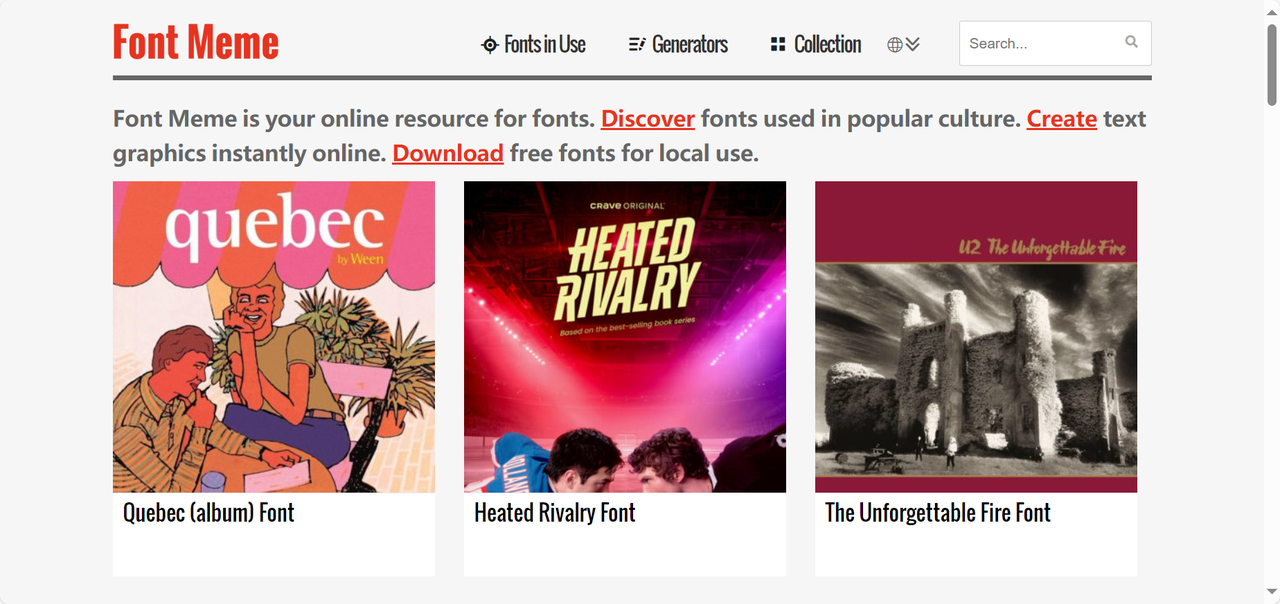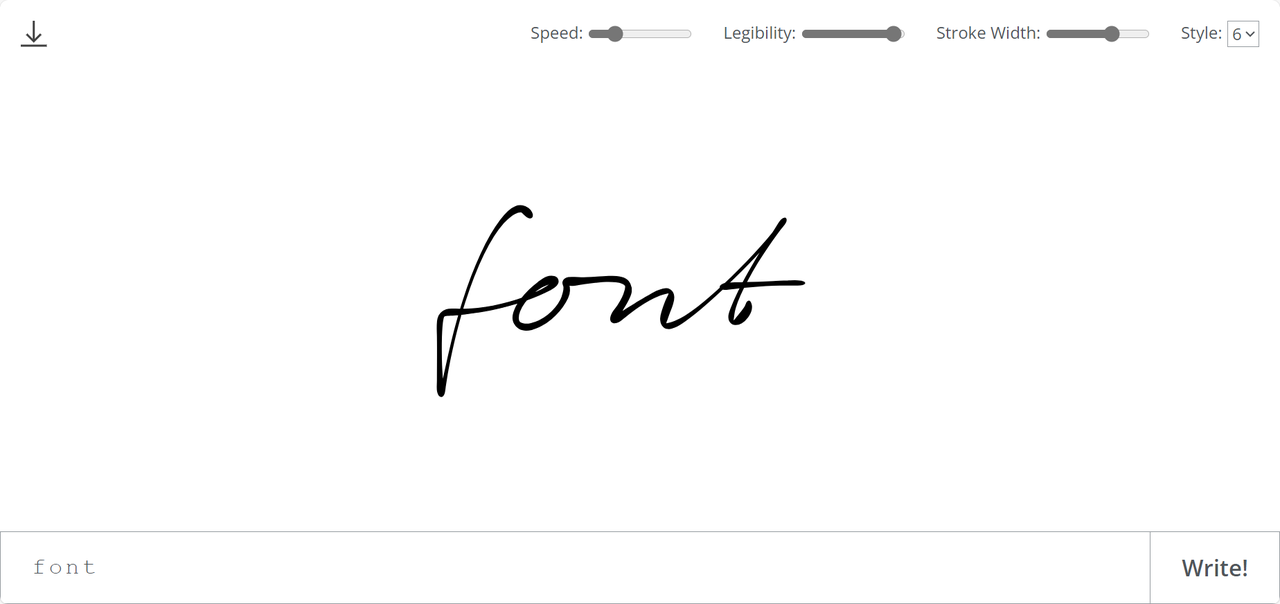
告别手写!毛笔字转换器:5款免费在线工具,文字秒变书法
近些年来,国风逐渐变成了很多人追求且喜爱的一个风格,国风设计慢慢走向全球化,毛笔字转换器则成为了国际设计师首选的创作神器。毛笔字会为平面设计增添一份手写的温度,也会为品牌设计注入东方美学,但其实很多人并不了解毛笔字的书写方式,毛笔字转换器可以轻松解决这种问题,让文字秒变书法!接下来,我会给大家介绍 5 款功能强大、各具特色的免费在线毛笔字转换工具,基于不同的技术路径,这些工具从笔刷模拟到 AI 生成,都可以帮助你高效获得想要的毛笔字,让你的创意不受技能的限制,打造更符合大众审美发国风作品!
一、字由
字由是我周围很多设计师朋友都喜欢的一个字体管理工具,能一键实现毛笔字的转换。在这里,你可以选择的毛笔字字体非常多,而且每个字体都标清了它的授权方式(免费商用、会员商用、单独授权),不用担心任何的侵权风险。
无需专业书法,在首页上方的工具栏,点击[全部字体],搜索“毛笔/ 书法 / 国潮”,或者是在字体类型部分选择“书法体”,即可筛选大量高质量模板,覆盖文艺、励志、武侠等场景,直接替换文字即可使用。我很喜欢字由的毛笔字体效果,它模拟了毛笔书写时的笔锋、浓淡等,效果很接近真实书写,适合古风设计、国风设计等。
这些字体资源里,挑选一个你喜欢的毛笔字模板,在字体详情页面,输出文字,就能转换为当前文字的字体效果,实时在线预览。
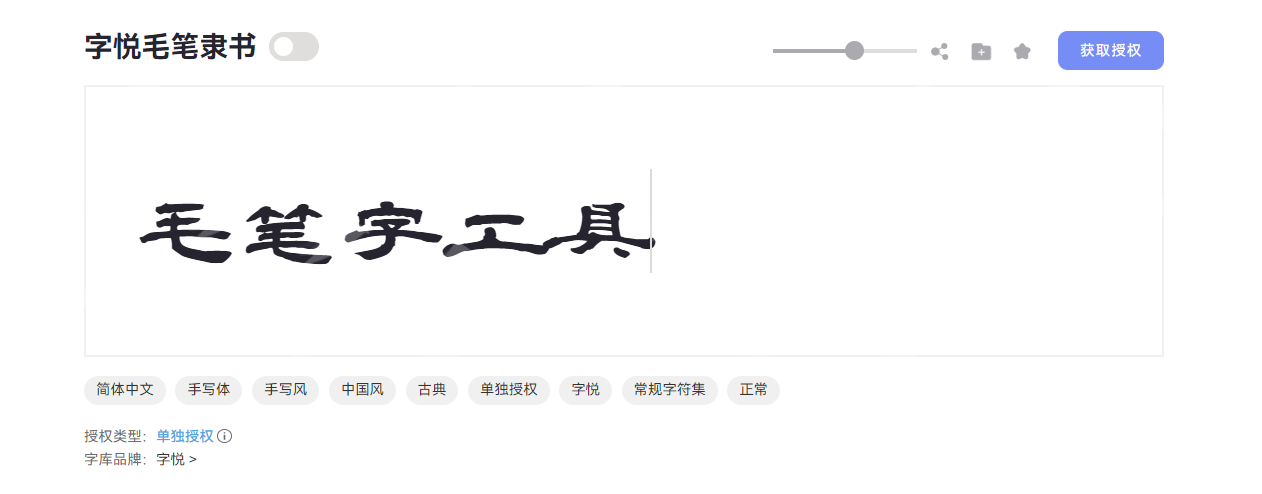
二、Font Meme
Font Meme 是一个字体资源与生成字体的网站,个人认为,它的资源库非常丰富,风格经典且识别度很高,生成的字体可直接用于基础设计。这款工具气势更倾向于为电影海报、品牌海报来提供适配的毛笔字体,虽然是国外的网站,页面布局清晰明了,对各种风格的字体进行了明确的划分,除此之外还有一些特殊效果的字体可以在线生成。
不过有一点需要注意,Font Meme 生成的是位图而非矢量图,放大可能会失真,影响呈现效果,而且不能调整笔触的细节,对于有创造性的设计师来说,它或许不是一个好的选择。
三、Calligrapher.ai
相比于其他工具,Calligrapher.ai 最大的优势在于它模拟了人类书写毛笔字的动态过程,你不仅可以看到最终形成的毛笔字体,也可以清晰看到它的书写过程,很适合用于艺术创作、邀请函、签名设计等。这款工具的操作非常简单,只需要在数去狂输入你想要的文字,在页面上方的工具栏调整书写速度、可读性、笔画粗细、风格,就可以获得很多种不同的毛笔字,它的笔触风格比较倾向于草书或行书,需要这类毛笔字的设计师们可以来尝试一下。
最关键的是,无需你掌握任何书法技巧,一键就能在线转换为毛笔字,而且完全免费,生成的字体可以下载为 SVG 格式,将其轻松应用于各种设计项目,不用担心清晰度问题。只不过它可以自定义的选项较少,Calligrapher.ai 更侧重于展示毛笔字体的形成过程,而非提供大量的毛笔字模板。它不仅是一个毛笔字转换器,更是一个激发创作灵感、提升设计效率的好帮手。
四、Fontspace
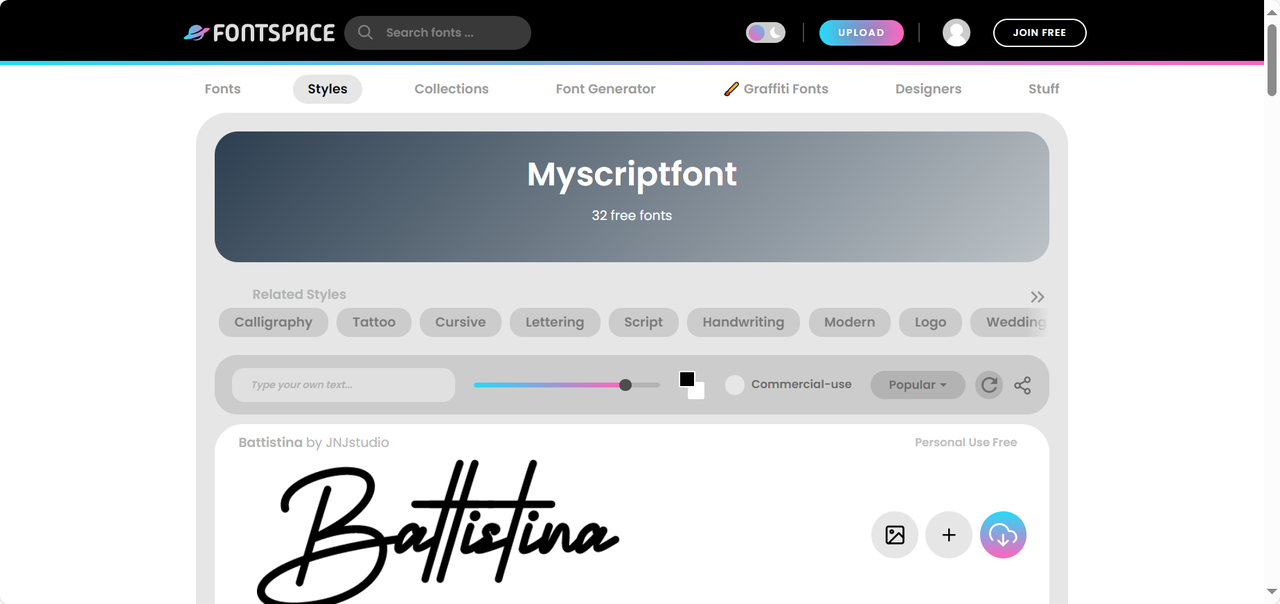
五、 DaFont
DaFont 本身不是一个毛笔字转换器,但它强大的筛选功能使它成为了一个寻找毛笔字体的绝佳工具。该工具同样拥有庞大的字体资源,而且包含大量由设计师上传的免费毛笔字体。DaFont 首页就对字体风格进行了细致的划分,帮助你快速定位想要的字体,想要毛笔字体可以直接选择“Script”分类下的“Calligraphy”或者“Handwritten”,然后直接在输入框输入你想要生成的文字内容,就可以一键预览所有风格的毛笔字体效果了。点击你看中的毛笔字体,还可以在线预览每个字母、数字、标点符号、拼音的实时效果。DaFont 也是需要下载字体到本地,并解压安装字体,某些时候可能还需要重启电脑才能使用新安装的字体,这一点可能比较占用时间。
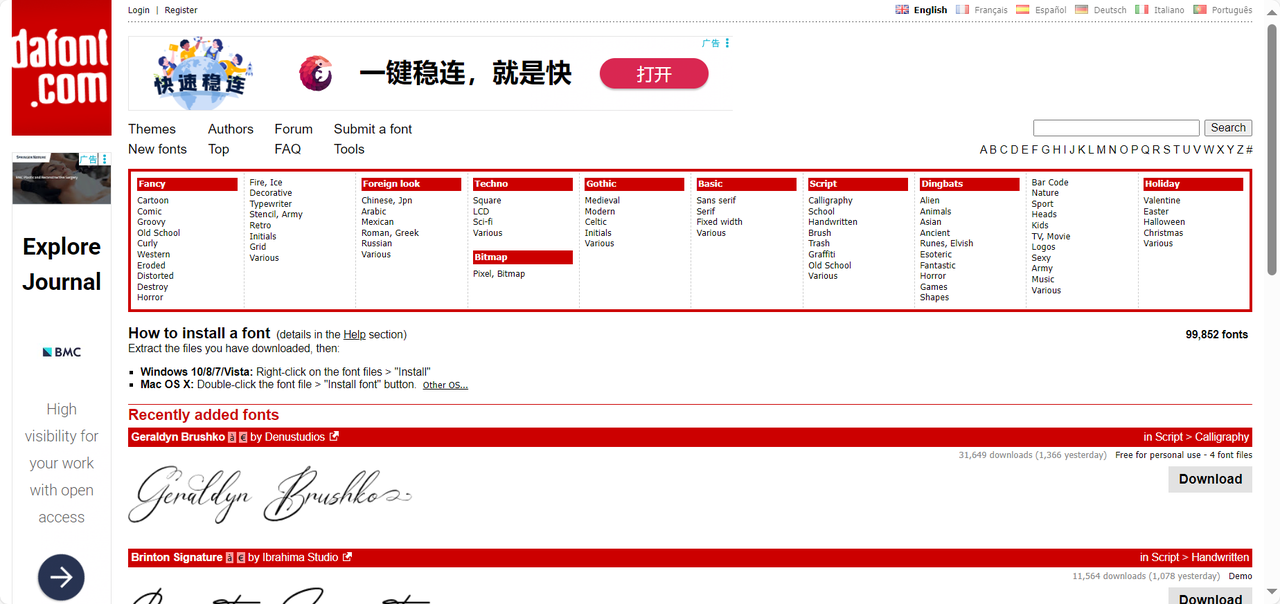
总而言之,这 5 款免费的毛笔字转换器能轻松实现你想要毛笔字体的需求,为你打开了毛笔书法艺术的大门。字由的毛笔字模板丰富多样,且无需下载安装,一键转换毛笔字;Font Meme 侧重于海报字体;Calligrapher.ai 可以查看毛笔字体的书写过程;Fontspace 和 DaFont 的字体选择更多,是强大的资源库,每个工具都提供了其独特的价值。借助这些工具,新手小白也可以轻松将文字转换为毛笔字,将我们的毛笔艺术融入创意项目!